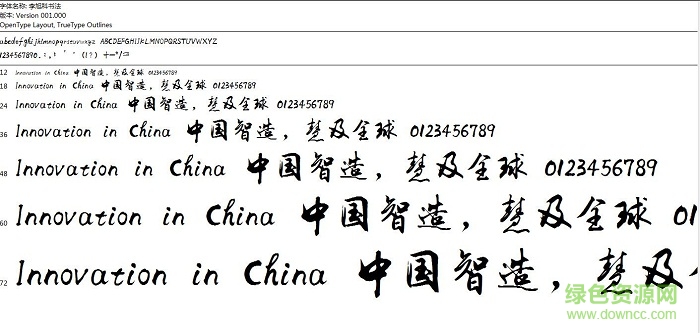
李旭科草書書法字體是一款筆勢連綿的草書字體,該字體氣勢雄健,飽滿張揚,線條如如行云流水,奔逸灑脫,一氣呵成,極具嗎,美感,用在小伙伴們趕緊下載吧!
初期的草書,打破隸書方整規(guī)矩嚴謹,是一種草率的寫法。稱為“章草”。章草是早期限草書和漢隸相融的雅化草體,波挑鮮明,筆畫鉤連呈“波”形,字字獨立,字形遍方,筆帶橫勢 。章草在漢魏之際最為盛行,后至元朝方復興,蛻變于明朝。